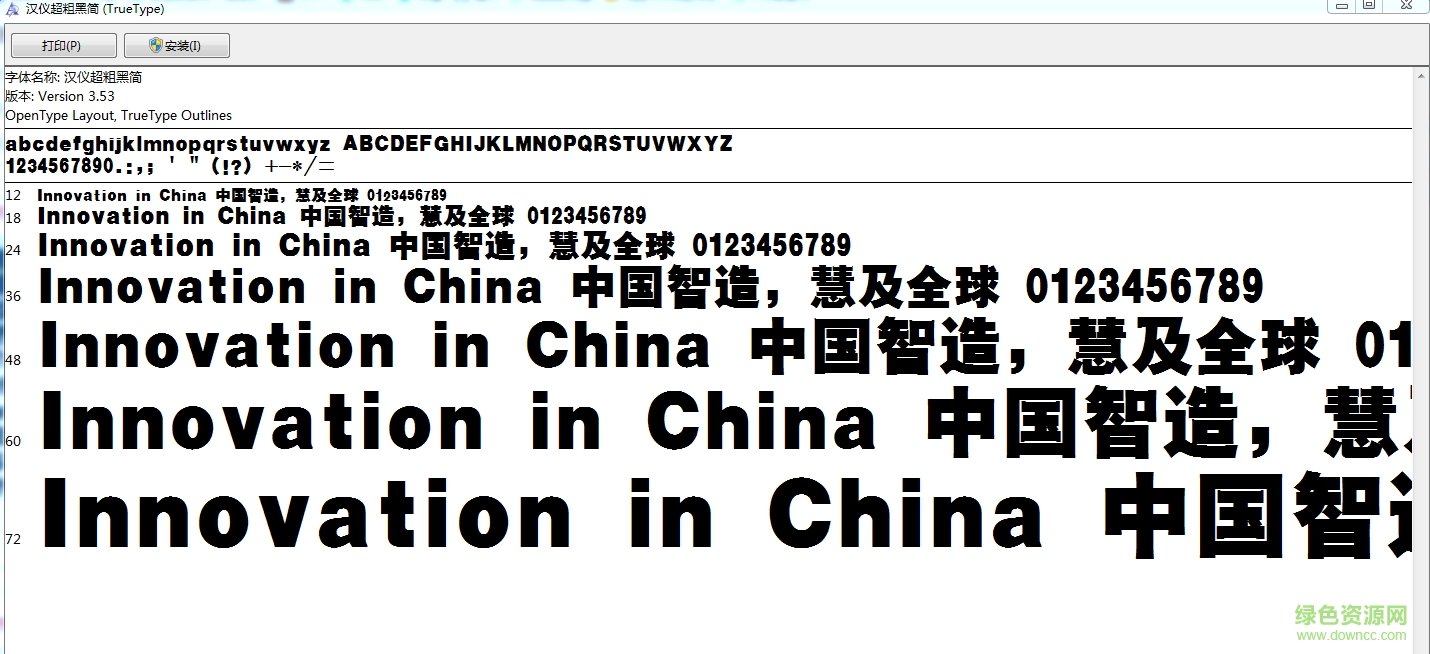
hyb0gj字體
字體hyb0gj漢儀字體中的一款哦,這款字體也叫漢儀超粗黑簡,使用范圍也是非常廣泛,運用到了各個領(lǐng)域中,感興趣的朋友趕緊來綠色資源網(wǎng)下載試玩吧!
hyb0gj字體介紹
漢儀超粗黑簡樸素大方、結(jié)構(gòu)嚴謹,非常引人注目,常用作印刷中穩(wěn)重、醒目的標題字。